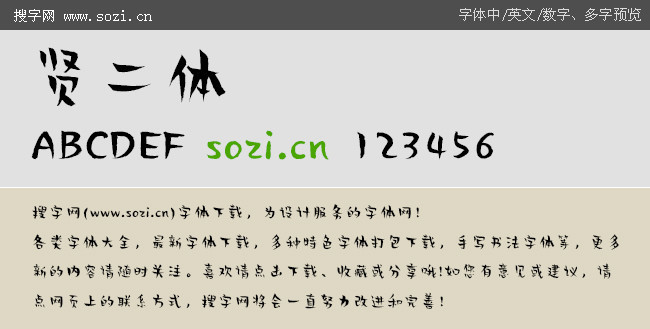
賢二體
搜字網(wǎng)提供一款賢二體中文字體下載,賢二體是北京龍泉寺動(dòng)漫中心與漢儀字庫(kù)聯(lián)合推出的一款商用免費(fèi)字體。賢二體的字形偏長(zhǎng),起筆收筆鋒利且粗細(xì)對(duì)比明顯,筆畫(huà)笨拙微帶曲線感。字體組合結(jié)構(gòu)松散,重心不穩(wěn),達(dá)到詼諧幽默,惹人喜愛(ài)的效果。適合應(yīng)用于海報(bào)設(shè)計(jì)、藝術(shù)設(shè)計(jì)、包裝設(shè)計(jì)等應(yīng)用